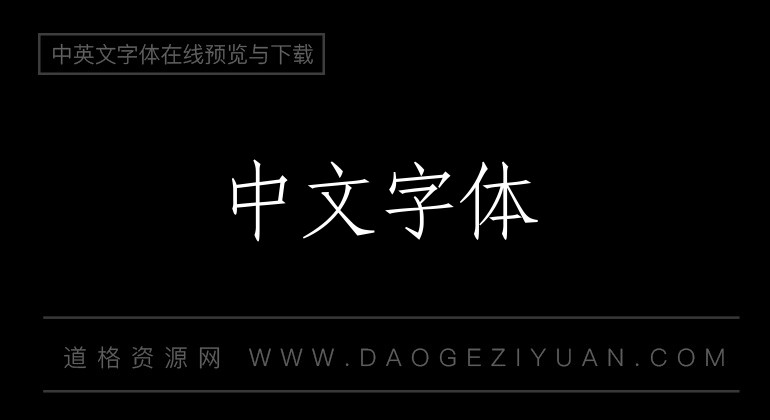
青鸟华光简仿宋一
青鸟华光简仿宋一是一款模仿宋体的简体字体,由青鸟字体设计工作室设计。它采用现代技术,结合传统笔画,创造出精美的字体,符合当今流行的简洁风格。它具有良好的可读性和可辨识性,适合用于报纸、杂志、书籍、广告等。
青鸟华光简仿宋一是一款非常不错的手写艺术字体,具有很好的视觉感,适合于文化类的宣传设计、商业类品牌的广告和产品包装设计以及个性化文字排版等较多场景。